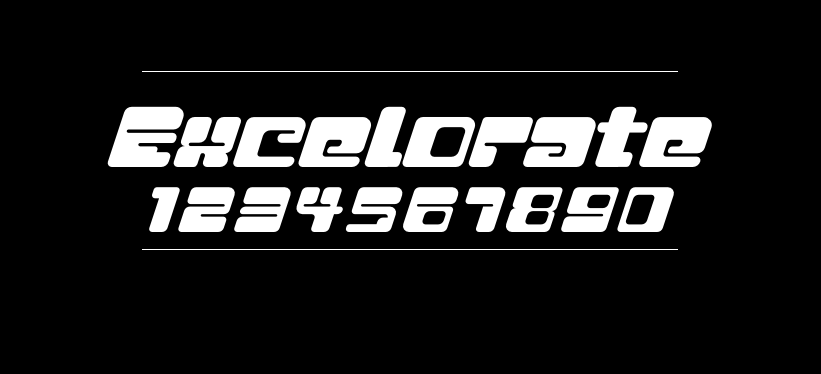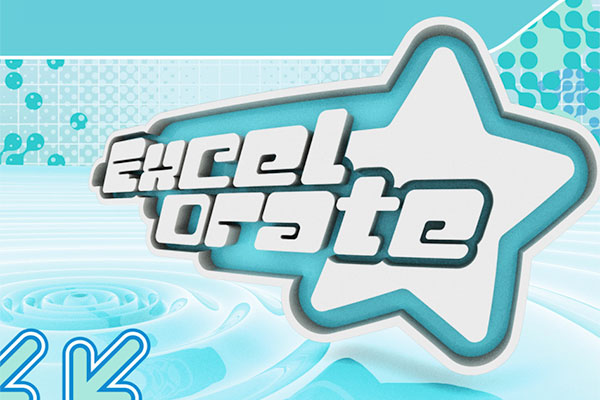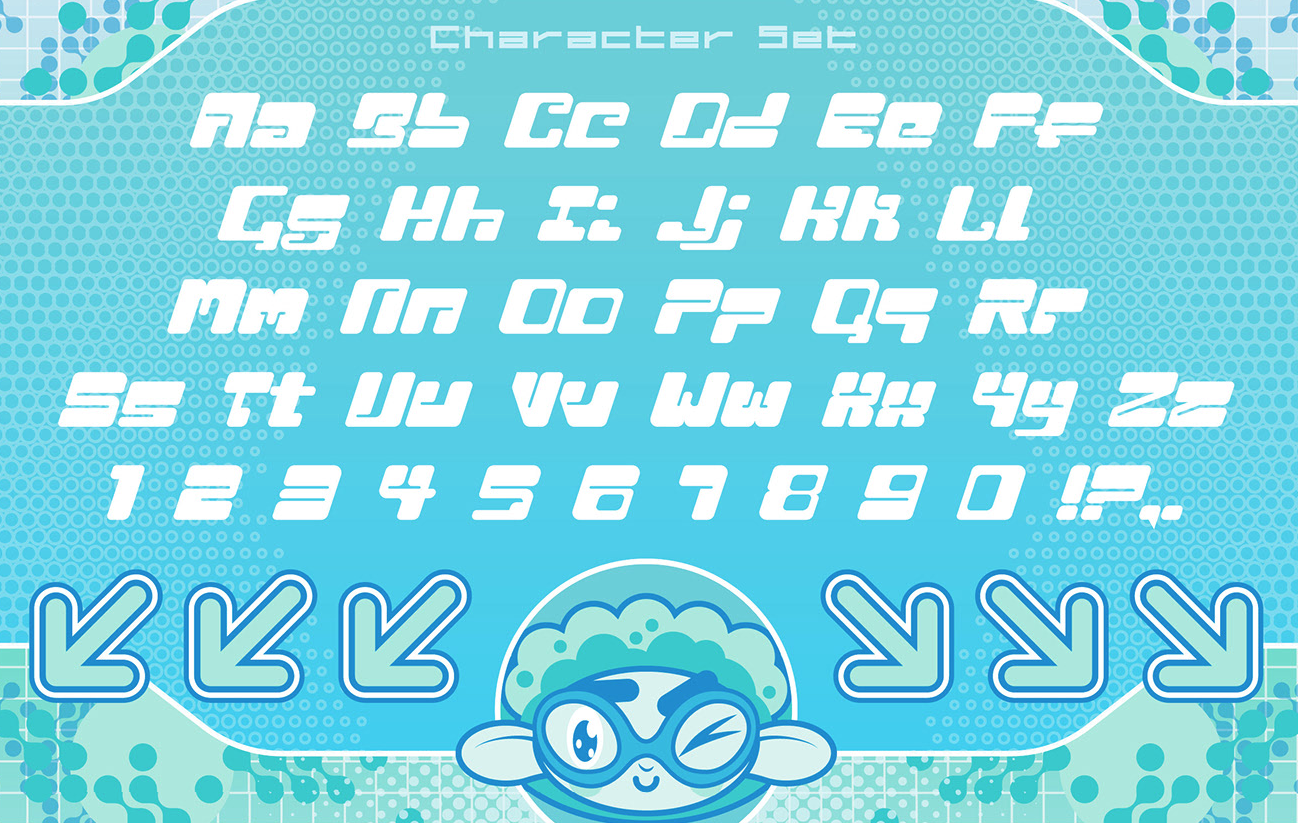
Excelorate
Excelorate字体介绍
Excelorate的作者是美国的Jorge Villarreal,作者称该字体的灵感来源于”Y2K美学“。至于Y2K是什么自由君一脸懵逼,于是百度了下,原来是这么回事:
“Y2K”中的“Y”代表“year”,“2K”即“2000”,这个名字源自“千年虫”,一个令世界人心惶惶,最终却没啥影响的电脑Bug:当时全世界都在担心千禧年到来,计算机会把2000年解析为1900 年,导致全球范围的大混乱。
但那又是个高科技大步流星,走入人类生活的关口,因此,在千禧年那一代人的想象、憧憬、危机感中,Y2K 美学得以诞生。
当然,Y2K并非一个严格意义上的设计风格,它更多指向了上世纪九十年代至二十一世纪的一种集体情感:经历着互联网泡沫的巅峰、感受着新旧纪元的交替、满怀着对未来的憧憬、不安。
继而,人们开始用金属材质、透明PVC、荧光色等代表高科技的视觉元素,来描绘那个未来世界:太空、高速、高科技、信息化、高度发展的乌托邦。
这么解释就对了,难怪依稀记得2000年时的对未来科技的想象,都是这样的形象。想当年的爆火的Disco舞曲视频,几乎都是这样的风格。
Excelorate字体应用示例